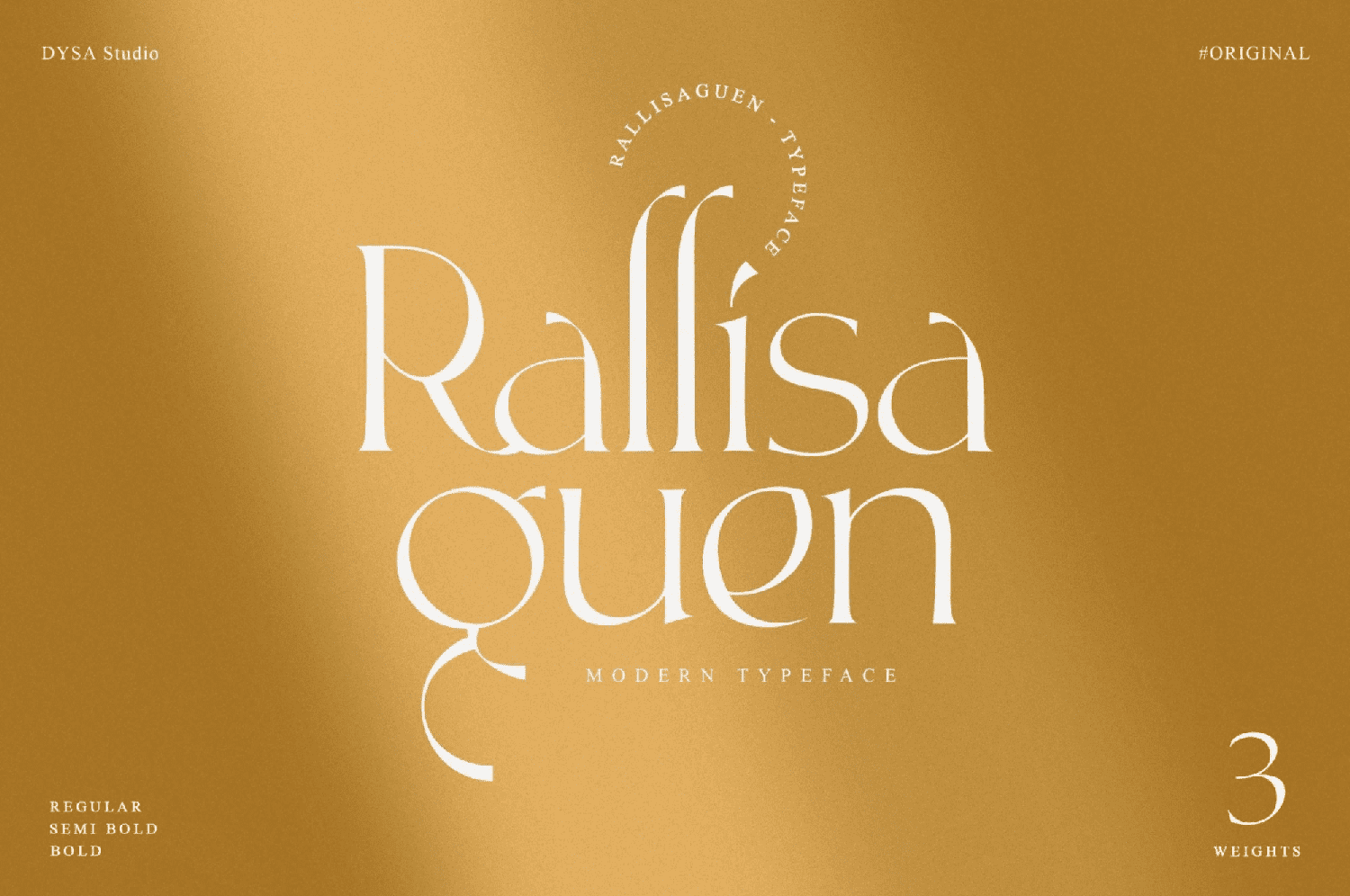
Название: Rallisaguen Font (2021)
Rallisaguen - это тонкий и элегантный шрифт с засечками, вдохновленный нестареющей классической каллиграфией.
Он прекрасно смотрится на различных дизайнах, требующих индивидуального стиля, таких как свадебные приглашения, благодарственные открытки, свадьбы, поздравительные открытки, логотипы и так далее.
Название: Rallisaguen Font (2021)
Rallisaguen - это тонкий и элегантный шрифт с засечками, вдохновленный нестареющей классической каллиграфией.
Он прекрасно смотрится на различных дизайнах, требующих индивидуального стиля, таких как свадебные приглашения, благодарственные открытки, свадьбы, поздравительные открытки, логотипы и так далее.